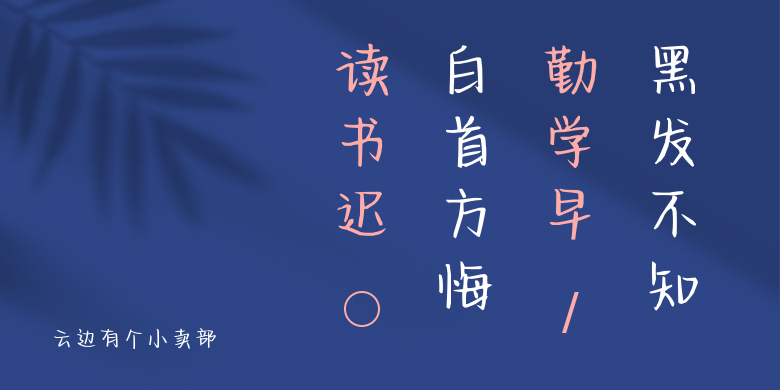
云边有个小卖部
云边有个小卖部,这款字体结构工整、笔画清晰,兼顾美观与易读性,适用于标题、正文、海报、包装、LOGO 等多种场景。字形优雅稳定,风格百搭耐看,适配日常排版与创意设计,让文字呈现更舒适、更具质感。云边有个小卖部一笔一画,皆是细节,以均衡的比例、流畅的线条打造舒适视觉体验,字形端正大气,风格简约现代。无论是商业设计、品牌宣传还是日常排版,都能轻松驾驭,让文字更有格调与力量。云边有个小卖部字体下载。